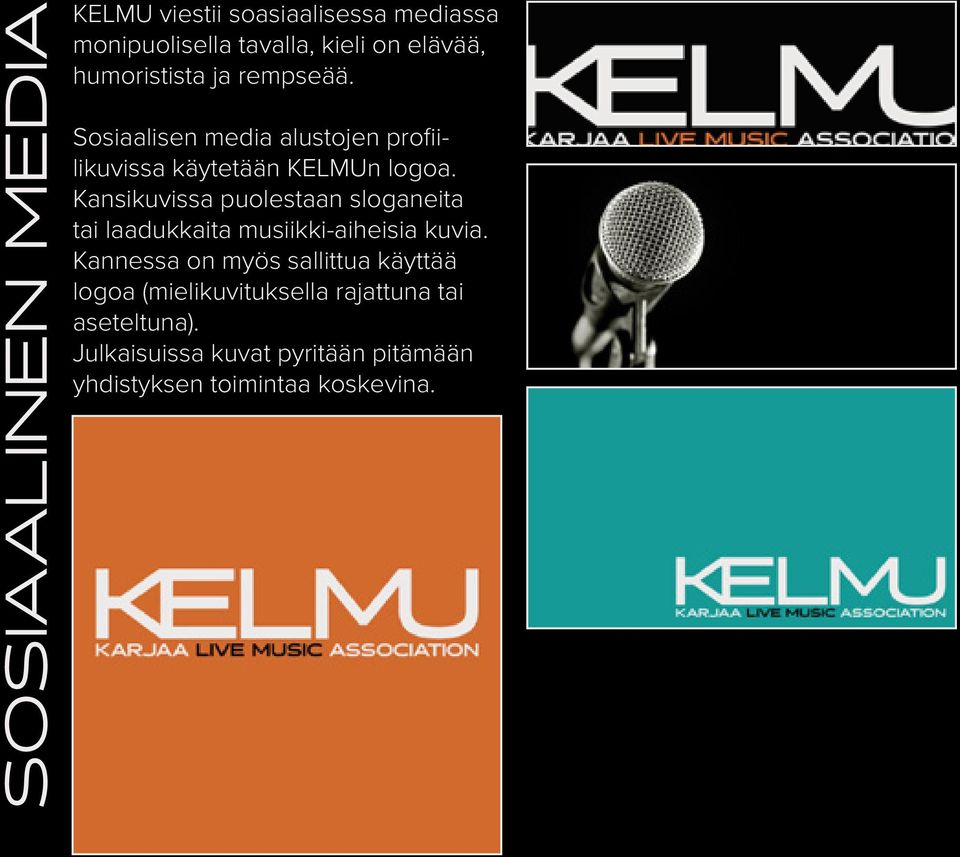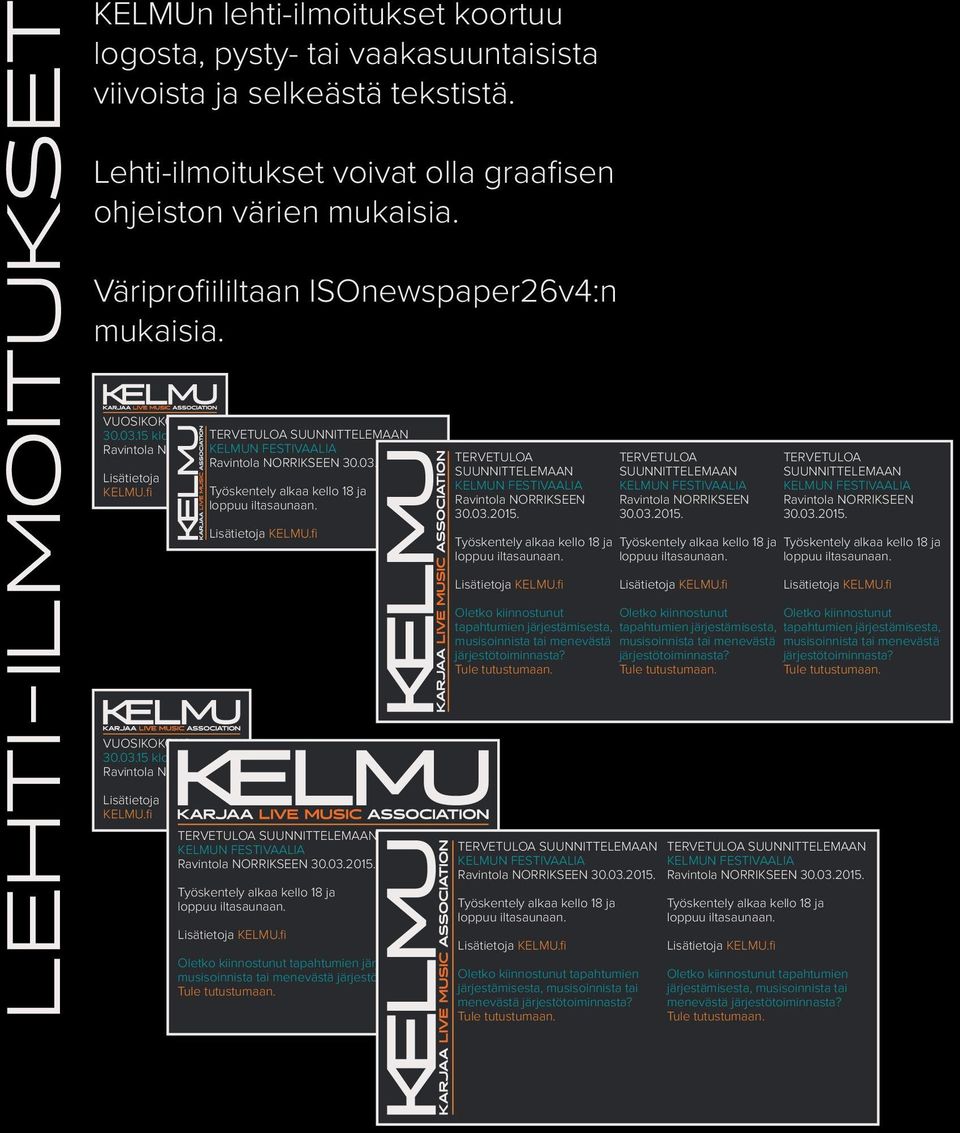
ESIPUHE. Graafisen ohjeiston peruselementit ovat: Kelmun tunnuskuva Kuvamaailma Typografia Tuotteet
3 ESIPUHE KELMUn graafinen ohje määrittelee yhdistyksen ilmeen niin painetussa kuin sähköisessä viestinnässä. Ohjeisto on tarkoitettu yhdistyksen toimijoille, aktiiveille ja yhteistyökumppaneille. Graafisen ilmeen suunnittelun lähtökohtana on ollut luoda graafinen ilme, joka on: selkeälinjainen, raikas ja desing-henkinen helposti hyödynnettävä musiikkialalle soveltuva yhdenmukainen KELMUn graafisen ohjeen linjauksia noudatetaan kaikessa painetussa ja sähköisessä viestinnässä. Ohjeistoon on koottu keskeiset viestinnässä käytettävät tuotteet, mutta ohjeistoa sovelletaan myös sellaisiin käyttötarkoituksiin, joita siinä ei ole erikseen mainittu. Graafisen ohjeiston peruselementit ovat: Kelmun tunnuskuva Kuvamaailma Typografia Tuotteet Ohjeistoon sisältyvien tuotteiden sähköiset tiedostot löytyvät KELMUn verkkosivuilta ja yhdsityksen käytössä olevat tiedostopohjat on tallennettu yhteisessäkäytössä olevaan pilvipalveluun. Lisätietoja graafisesta ohjeistosta ja KELMUn viestinnästä antaa yhdistyksen puheenjohtaja Mikko Vainio
4 VÄRIT KELMU käyttää viestinnässään viittä pääväriä, joita voidaan yhdistää liukuvärein. Väreistä on sallittua käyttää myös haalennettuja sävyjä. 35% 55% 85%. Lisäksi asiakirja pohjissa käytetaan paperin väriä. Tekstissä voidaan käyttää kaikkia värejä, kuitenkin niin että teksti erottuu taustastaan selvästi. Musta Pantone coated: K100 C Pantone uncoated: K100 U CMYK: HSB: RGB: HEX: # Oranssi Turkoosi Harmaa Valkoinen Pantone coated: Pantone uncoated: CMYK: HSB: Pantone 1585 C Pantone 1585 U RGB: HEX: #e86b1e Pantone coated: Pantone 3272 C Pantone uncoated: Pantone 3272 U CMYK: HSB: RGB: HEX: #009f99 Pantone coated: Pantone uncoated: CMYK: HSB: 208, 1, 54 Pantone 423 C Pantone 423 U RGB: HEX: #898a8b Pantone coated: Pantone uncoated: CMYK: HSB: Pantone P169-1 C Pantone P169-1 U RGB: HEX: #eceae9
5 SÄVYT Musta Oranssi Turkoosi Harmaa Valkoinen 85% 55% 35%
6 LOGO Kelmun logo pohjautuu HALOGEN Relular -fonttiin. KE ja MU kirjainparit on yhdistettu. KELMUn viestinnässä käytetään logotiedostoja, Tekstinä voidaan myös käyttää kyseistä fonttia sana KELMU versaalein kirjoitettuna. KELMU sanan kanssa päätteet kirjoitetaan pienellä ilman kaksoispistettä. Esimerkki KELMUn tai KELMUsta. Logoa ei saa käyttää moniväristen sekavien kuvien kanssa ilman taustaa. Logoon ei saa yhdsitää muita kuvioita. Jos logoa käytetään ilman taustaa, sen tulee erottua selkeästi. Logon taustan värinen suoja-alue on 2mm. Logo-tiedostoissa ei ole suoja-aluetta käytön helpottamiseksi (kuten oikealla). Logon oikeaoppinen käyttö:
7 TUOTEMERKKI Tuotemerkkiä voidaan käyttää selkeyttä ja yksinkertaisuutta vaativissa kohteissa. Esimerkiksi laitteistomerkkaukset. Tuotemerkkiä ei saa käyttää moniväristen sekavien kuvien kanssa ilman taustaa. Tuotemerkkiin ei saa yhdsitää muita kuvioita. Jos logoa käytetään ilman taustaa, sen tulee erottua selkeästi. Tuotemerkinn taustan värinen suoja-alue on 2mm. Logo-tiedostoissa ei ole suoja-aluetta käytön helpottamiseksi (kuten oikealla). Tuotemerkin oikeaoppinen käyttö:
8 KIRJAISIMET KELMU käyttää viestinnässään pääsääntöisesti 2 fonttia. Toinen on otsikointia ja toinen leipätekstiä varten. Perusviestinnässä käytetään määriteltyjä vaihtoehtoja, mutta esimerkiksi monipuolisempaa typografiaa vaativissa töissä voidaan hyödyntää kirjaisimien perheitä. Tällaisia tapauksia voi olla esimerkiksi tapahtumajulisteet. OTSIKKOTEKSTI Halogen Regular Fontti on selkeälinjainen, monikäyttöinen kirjaisin, jonka Neil Summerour. Hän on asunut USAn Georgiassa, viettänyt aikaa myös Takamatsussa Japanissa. Hän on Positype yhtiönsä kanssa julkaissut yli 60 fonttiperhettä ja luonut lukuisia kustomoituja leikkauksia asiakkailleen maailman laajuisesti. abcdefghijklmnopqrstuyxzåäö ABCDEFGHIJKLMNOPQRSTUYXZÅÄÖ LEIPÄTEKSTI Proxima Nova Light Fontin on suunnitellut Mark Simonson Studio vuonna Kirjaisin perustuu Proxima Sans -fonttiin (1994). Proxima Nova vastasi kysyntään Futuran ja Akzidenz Grotesk -fonttien välissä. Mark Simonson on lähtöisin Minnesotasta, USAsta, jossa hän pääsi tekemään paikallisen radion palveluksessa useita aikakauslehtiä. Nykyään hän suunnitellut yli 100 fonttia. abcdefghijklmnopqrstuyxzåäö ABCDEFGHIJKLMNOPQRSTUYXZÅÄÖ
9 KUVAKIELI KELMU käyttää kuvakielenään musiikkiaiheisia kuvia, jotka on laadukkaasti tuotettuja. Aiheina on soittimet, tapahtumat, muusikot. Julkaisuiden kuvakieleen kiinnitetään tarkempaa huomiota. Kuvissa pyritään säiluttämään musta tausta. Kuvia voidaan rajata mielikuvituksellisesti. Sosiaalisen median kuvat on vapaamuotoisempia, niissä pyritään esittämään ajankohtaisesti tapahtumia, yksityiskohtia ja yhdistyksen aktiiveja työnsä/tekemisiensä äärellä.
10 SLOGAN KELMU käyttää sloganeita tuodakseen perustehtäväänsä tai toimintaperiaatteitaan julki. Sloganit kirjoitetaan otsikkofontilla ja versaalina. KELMU MUSIIKIN ASIALLA JO VUODESTA 1998 KELMU SE ON MUSIIKKIA! KELMU HAISTA MUSIIKKI! KELMU RAASEPORILAISTEN MUSADIGGAREIDEN MUSANIKKARI MUSIIKKI KUULUU KAIKILLE ELÄVÄÄ MUSIIKKIA ELÄVÄLLE KAUPUNGILLE ELÄVÄN MUSIIKIN YHDISTYS ON SINUA VARTEN ELÄMÄ ILMAN MUSIIKKIA ON KUIN KELMU ILMAN ÄÄNENTOISTOA VAPAUS MUSIIKISSA VAPAUTTA JA MUSIIKKI = KELMU
11 SOSIAALINEN MEDIA KELMU viestii soasiaalisessa mediassa monipuolisella tavalla, kieli on elävää, humoristista ja rempseää. Sosiaalisen media alustojen profiilikuvissa käytetään KELMUn logoa. Kansikuvissa puolestaan sloganeita tai laadukkaita musiikki-aiheisia kuvia. Kannessa on myös sallittua käyttää logoa (mielikuvituksella rajattuna tai aseteltuna). Julkaisuissa kuvat pyritään pitämään yhdistyksen toimintaa koskevina.
12 LEHTI-ILMOITUKSET KELMUn lehti-ilmoitukset koortuu logosta, pysty- tai vaakasuuntaisista viivoista ja selkeästä tekstistä. Lehti-ilmoitukset voivat olla graafisen ohjeiston värien mukaisia. Väriprofiililtaan ISOnewspaper26v4:n mukaisia. VUOSIKOKOUS klo TERVETULOA SUUNNITTELEMAAN Ravintola NORRIS KELMUN FESTIVAALIA Ravintola NORRIKSEEN Lisätietoja KELMU.fi Työskentely alkaa kello 18 ja loppuu iltasaunaan. Lisätietoja KELMU.fi VUOSIKOKOUS klo Ravintola NORRIS Lisätietoja KELMU.fi TERVETULOA SUUNNITTELEMAAN KELMUN FESTIVAALIA Ravintola NORRIKSEEN Työskentely alkaa kello 18 ja loppuu iltasaunaan. Lisätietoja KELMU.fi Oletko kiinnostunut tapahtumien järjestämisesta, musisoinnista tai menevästä järjestötoiminnasta? Tule tutustumaan. TERVETULOA SUUNNITTELEMAAN KELMUN FESTIVAALIA Ravintola NORRIKSEEN Työskentely alkaa kello 18 ja loppuu iltasaunaan. Lisätietoja KELMU.fi Oletko kiinnostunut tapahtumien järjestämisesta, musisoinnista tai menevästä järjestötoiminnasta? Tule tutustumaan. TERVETULOA SUUNNITTELEMAAN KELMUN FESTIVAALIA Ravintola NORRIKSEEN Työskentely alkaa kello 18 ja loppuu iltasaunaan. Lisätietoja KELMU.fi Oletko kiinnostunut tapahtumien järjestämisesta, musisoinnista tai menevästä järjestötoiminnasta? Tule tutustumaan. TERVETULOA SUUNNITTELEMAAN KELMUN FESTIVAALIA Ravintola NORRIKSEEN Työskentely alkaa kello 18 ja loppuu iltasaunaan. Lisätietoja KELMU.fi Oletko kiinnostunut tapahtumien järjestämisesta, musisoinnista tai menevästä järjestötoiminnasta? Tule tutustumaan. TERVETULOA SUUNNITTELEMAAN KELMUN FESTIVAALIA Ravintola NORRIKSEEN Työskentely alkaa kello 18 ja loppuu iltasaunaan. Lisätietoja KELMU.fi Oletko kiinnostunut tapahtumien järjestämisesta, musisoinnista tai menevästä järjestötoiminnasta? Tule tutustumaan. TERVETULOA SUUNNITTELEMAAN KELMUN FESTIVAALIA Ravintola NORRIKSEEN Työskentely alkaa kello 18 ja loppuu iltasaunaan. Lisätietoja KELMU.fi Oletko kiinnostunut tapahtumien järjestämisesta, musisoinnista tai menevästä järjestötoiminnasta? Tule tutustumaan.
13 JÄSENKORTTI KELMUn jäsenkortti 90x50mm. Mikko Vainio JÄSENKORTTI 2015 KARJAA LIVE MUSIC ASSOCIATI- ON KARJAA LIVE MUSIC ASSOCIATION KAR- JAA LIVE MUSIC ASSOCIATION KARJAA LIVE MU- SIC ASSOCIATION KARJAA LIVE MUSIC ASSO- CIATION KARJAA LIVE MUSIC ASSOCIATION KAR- JAA LIVE MUSIC ASSOCIATION KARJAA LIVE MU- SIC ASSOCIATION KARJAA LIVE MUSIC AS- SOCIATION KARJAA LIVE MUSIC ASSOCIA- TION KARJAA LIVE MUSIC ASSOCIATION KAR- JAA LIVE MUSIC ASSOCIATION KARJAA LIVE MU SIC ASSOCIATION KARJAA LIVE MUSIC ASSO CIATION KARJAA LIVE MUSIC ASSOCIATION KAR- JAA LIVE MUSIC ASSOCIATION KARJAA LIVE MU SIC ASSOCIATION KARJAA LIVE MUSIC AS SOCIATION KARJAA LIVE MUSIC ASSOCIA TION KARJAA LIVE MUSIC ASSOCIATION KAR JAA LIVE MUSIC ASSOCIATION KARJAA LIVE M SIC ASSOCIATION KARJAA LIVE MUSIC AS CIATION KARJAA LIVE MUSIC ASSOCIATI KARJAA LIVE MUSIC ASSOCIATION KAR JAA LIVE MUSIC ASSOCIATION KARJAA LIVE MUSIC ION KARJAA LIVE MUSIC ASSOC A LIVE MUSIC ASSOCIATI IC ASSOCIATION KA N KARJAA LIV USIC A IA